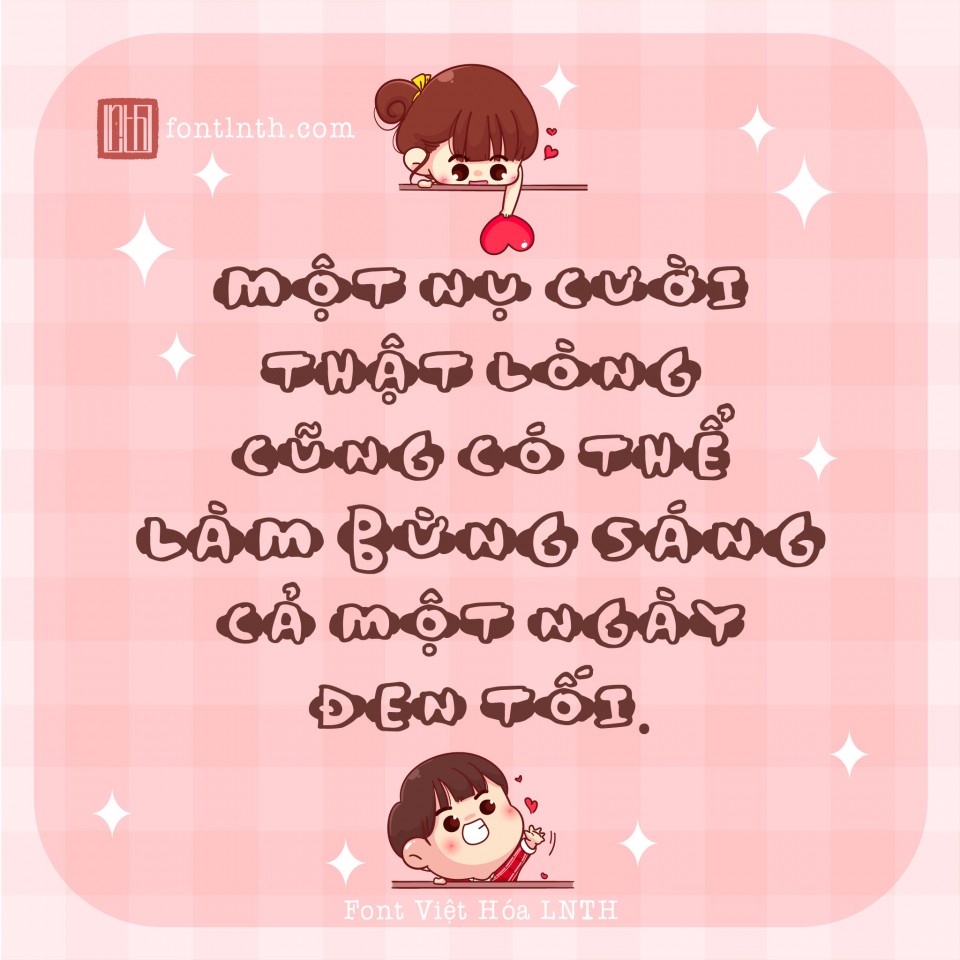
Trong thế giới đồ họa hiện đại, việc lựa chọn một bộ Font Chữ phù hợp đóng vai trò quyết định đến tính thẩm mỹ và thông điệp của sản phẩm. Một trong những cái tên đang thu hút sự chú ý của cộng đồng thiết kế chính là Font việt hóa LNTH Chicken Waffles. Đây là một phông chữ mang phong cách viết tay đầy ngẫu hứng, gợi lên sự trẻ trung và ấm áp. Nhờ quá trình việt hóa tỉ mỉ, người dùng tại Việt Nam có thể dễ dàng sử dụng đầy đủ các dấu câu mà không lo lỗi hiển thị, giúp quy trình sáng tạo trở nên mượt mà và chuyên nghiệp hơn bao giờ hết.
Đặc điểm nổi bật của Font việt hóa LNTH Chicken Waffles
Phong cách thiết kế độc đáo
Bộ Font việt hóa LNTH Chicken Waffles sở hữu những đường nét uốn lượn tự nhiên, mô phỏng lại nét bút lông mềm mại. Kiểu dáng của nó gợi nhớ đến những thực đơn tại các quán cà phê hay nhãn dán thủ công, tạo cảm giác gần gũi và thân thiện cho người xem. Các ký tự được thiết kế với độ dày vừa phải, giúp văn bản dễ đọc ngay cả trên nền hình ảnh phức tạp.
Tính ứng dụng linh hoạt trong đời sống
Nhờ vẻ ngoài năng động, font chữ này cực kỳ phù hợp cho các dự án thiết kế thiệp mời, bìa sách thiếu nhi, hay các bài thuyết trình học đường. Ngoài ra, các nhà sáng tạo nội dung trên mạng xã hội cũng thường xuyên sử dụng phông chữ này để làm nổi bật tiêu đề video hoặc ảnh bìa trang cá nhân. Sự linh hoạt giữa nét cổ điển và hiện đại giúp nó không bao giờ lỗi mốt.
Hướng dẫn sử dụng và kết luận
Để tận dụng tối đa vẻ đẹp của bộ chữ, bạn nên kết hợp nó với các tông màu pastel hoặc màu gỗ tự nhiên. Đừng quên kiểm tra khoảng cách giữa các chữ cái để đảm bảo bố cục hài hòa nhất. Hy vọng rằng bộ Font Miễn Phí, Font Việt Hóa, Font việt hóa LNTH Chicken Waffles sẽ trở thành nguồn cảm hứng mới cho các dự án của bạn. Chúc bạn có những trải nghiệm thiết kế tuyệt vời và đầy thú vị.